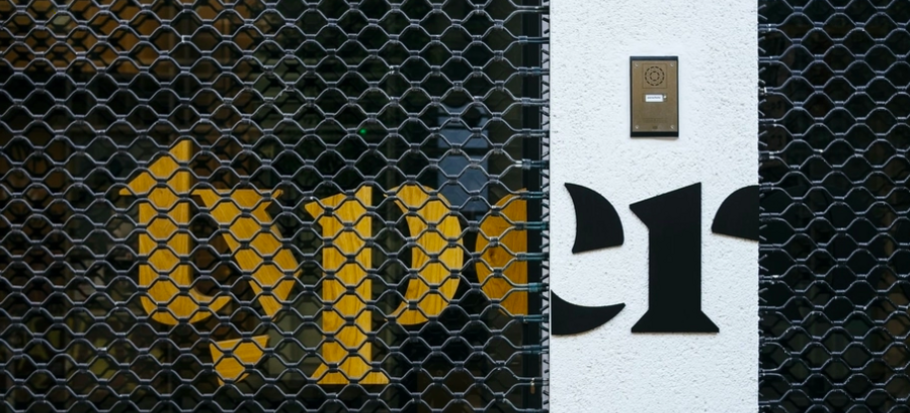
Variable Fonts: Mehr Stil für die visuelle Stimme Ihrer Marke
ihre Typografie und öffnen ein neues ästhetisches Universum.. “
Die meisten Designer haben zwar schon von variablen Fonts gehört, aber viele betrachten sie immer noch als eine unreife Technologie, die vor allem Experimentierfreudigen und Schrift-Nerds vorbehalten ist. Tatsächlich ist die Variable-Font-Technologie ausgereift und erfolgreich, weil sie Kreativen die vollständige Kontrolle über ihr Design geben. Sie eröffnen zukunftsorientierten Marken eine Reihe von Möglichkeiten und lösen zahlreiche Probleme, mit denen sich Entwickler beim Coding von Fonts im Web lange herumgeschlagen haben.
Kürzlich hielt Tom Rickner, Creative Type Director bei Monotype, im Rahmen des „Creative Month“ des The One Club For Creativity (vergleichbar mit dem ADC in Deutschland) einen Vortrag über die aktuellen und zukünftigen Möglichkeiten variabler Schriften und demonstrierte live, was variable im Gegensatz zu statischen Schriften alles leisten. Sehen Sie sich die Aufzeichnung der Präsentation an.